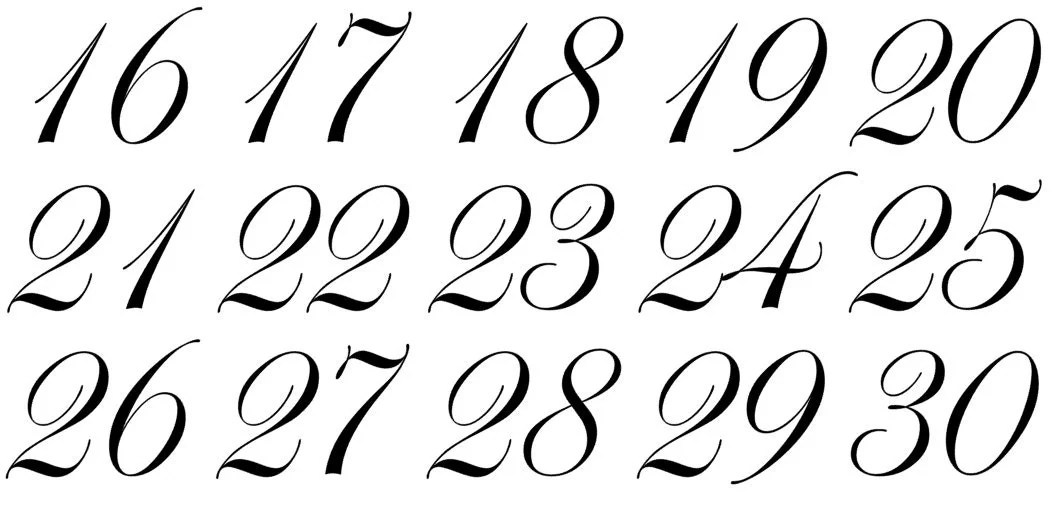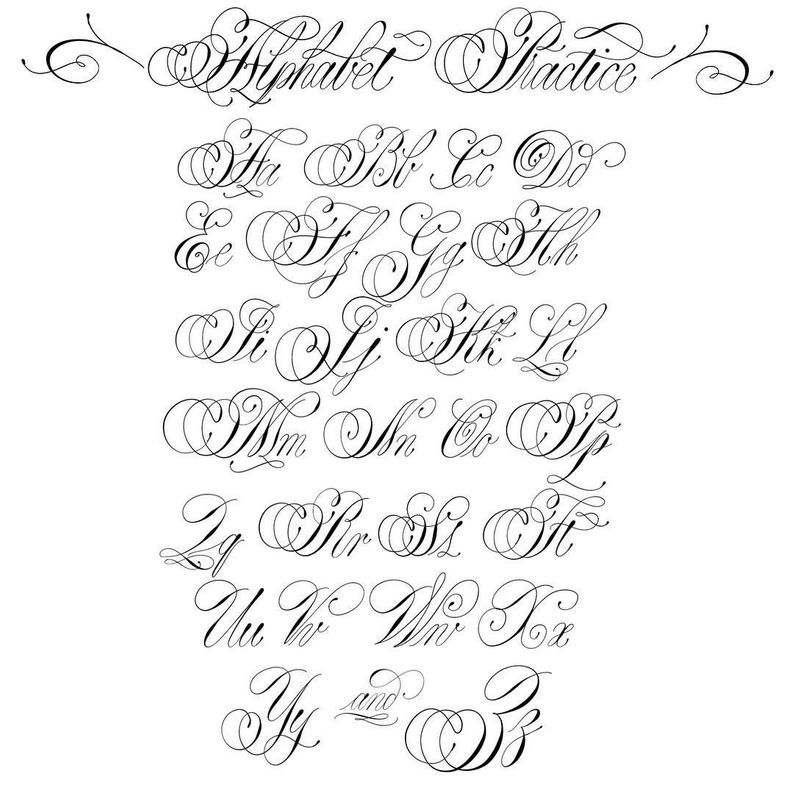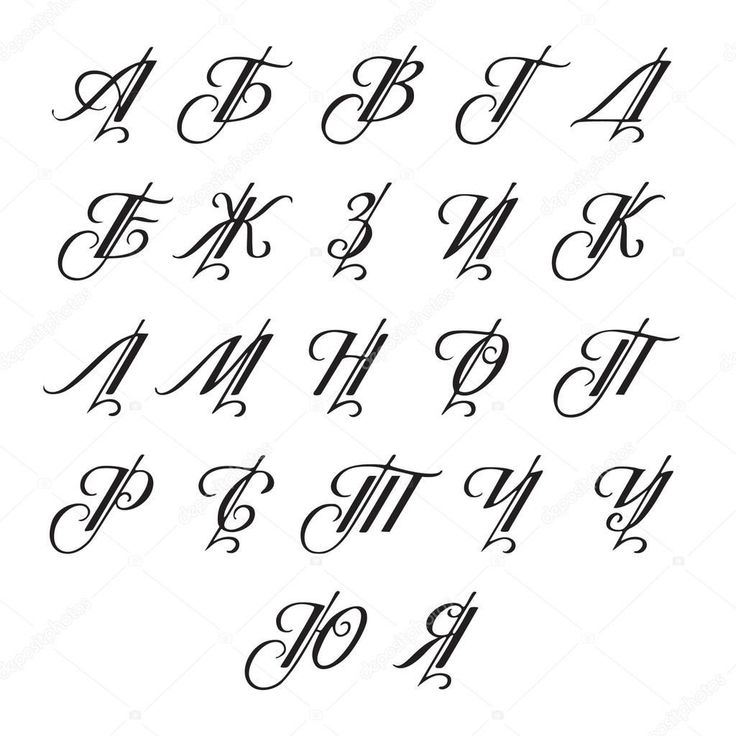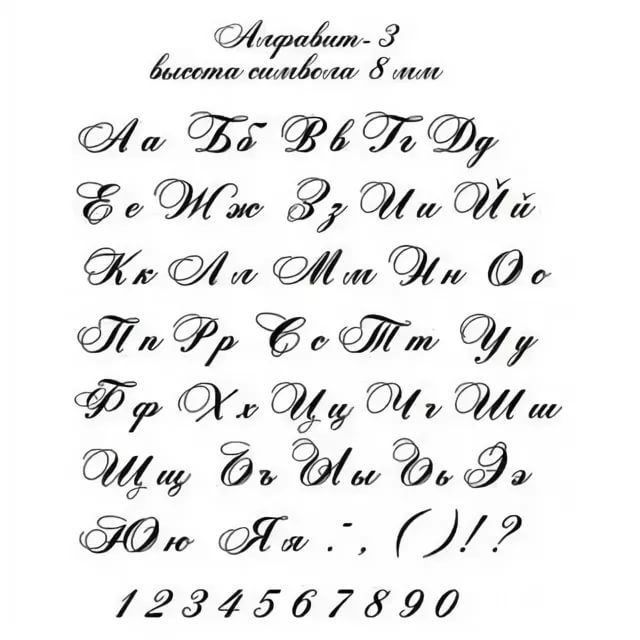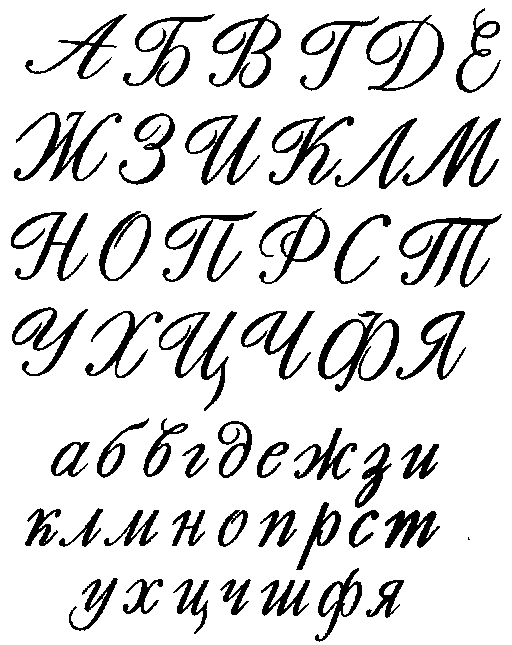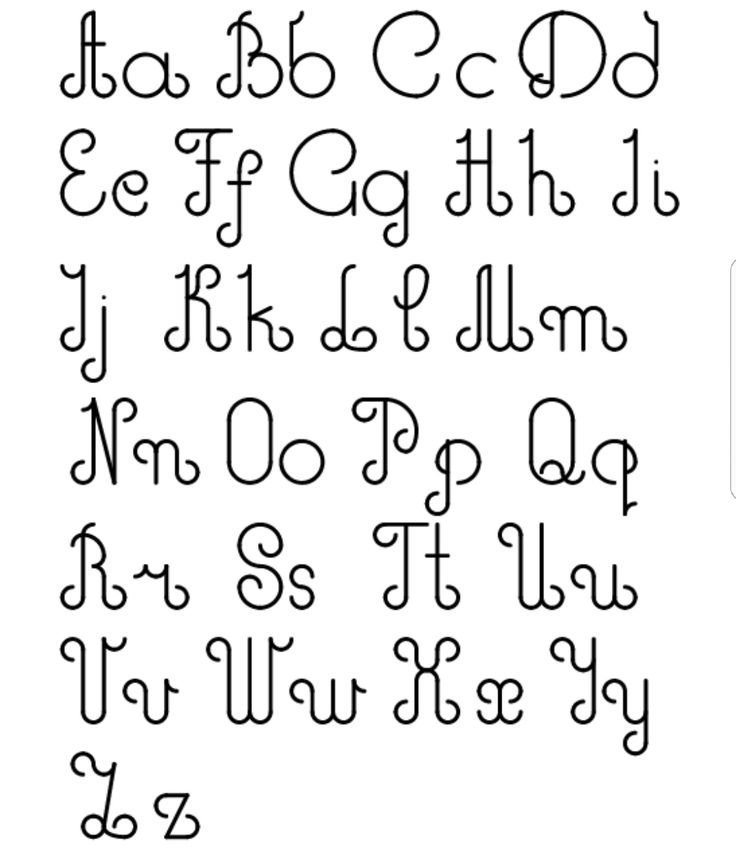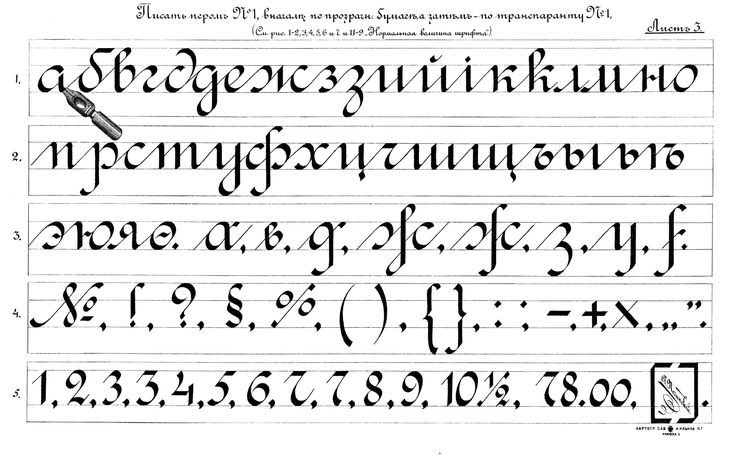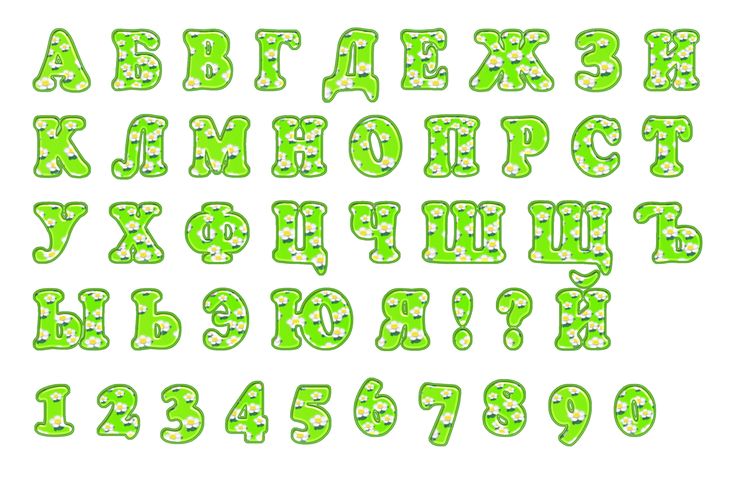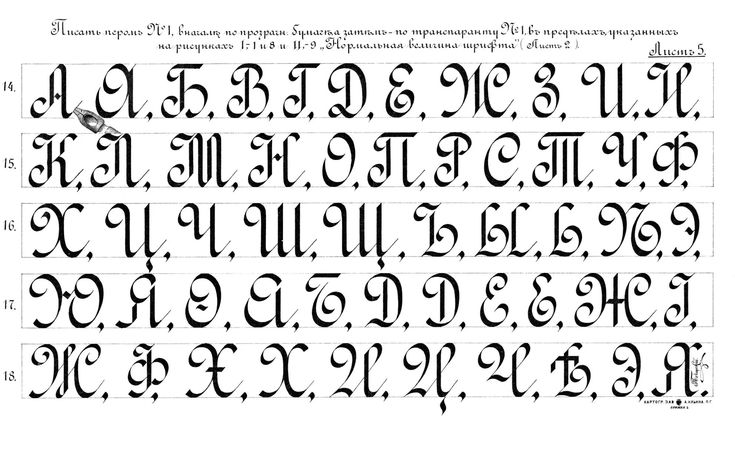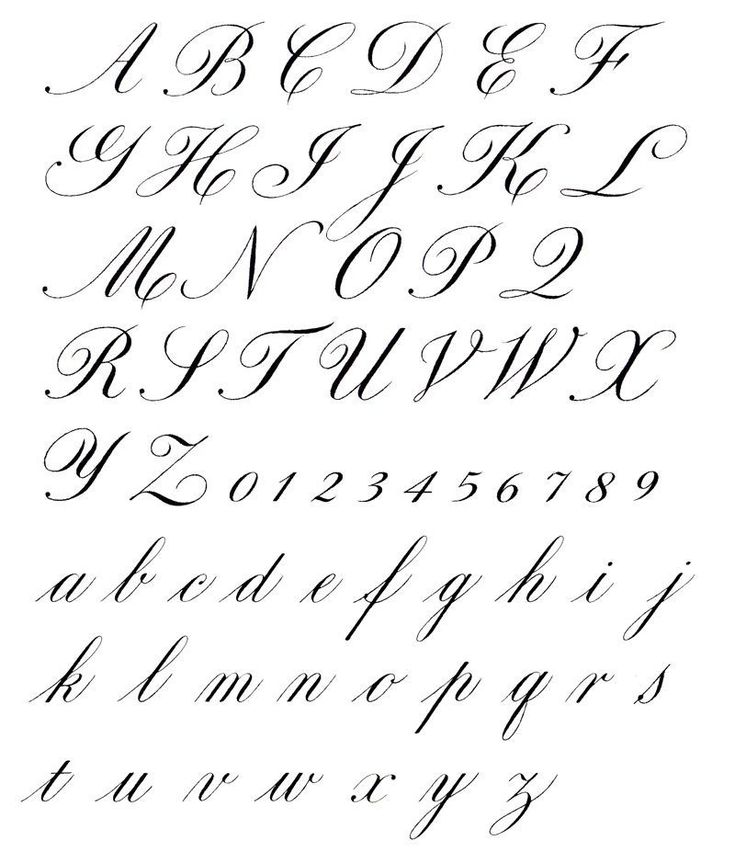
Красивые шрифты онлайн, сделать красивый текст
Шрифты являются важной частью типографики вашего проекта. Слишком причудливые буквы могут быть трудны для восприятия, слишком простые вызовут скуку и отобьют желание читать дальше. Вот почему следует максимально сосредоточиться на выборе красивых шрифтов, которые будут разборчивыми и привлекательными. Правильный фонт обеспечит эстетическую ценность контента, настроит общий тон проекта и пользовательский интерес.
Среди них вы найдете буквенно-цифровые наборы для любого случая и любой потребности, почти все начертания доступны для скачивания бесплатно. Нужен ли вам фонт для оформления проекта или просто хотите посмотреть, как будет выглядеть надпись красивым шрифтом онлайн — на нашем сайте есть все, что нужно. С таким количеством гарнитур вы обязательно найдете идеальный вариант для работы
Если никак не получается самостоятельно подобрать нужный стиль для дизайна текста, не волнуйтесь.
Мы позаботились о решении проблемы. На этой странице представлено много красивых шрифтов как для скачивания, так и для просмотра онлайн.
Все они отличаются индивидуальностью и разнообразием: среди них есть версии с засечками и без, рукописные, готические, курсив, печатные с поддержкой кириллицы. Цель использования таких фонтов — привлечь внимание оригинальным внешним видом. С помощью красивых шрифтов можно сделать авторскую надпись или заголовок, выделить часть текста, придав ему неповторимость и уникальность. Но для использования в основном контенте они не годятся.
Зачастую сложно определить, как будет смотреться тот или иной набор букв в проекте. Для этого нужно обладать большим опытом и фантазией. Если вы начинающий дизайнер или неискушенный любитель, попробуйте наш генератор красивых шрифтов онлайн. Просто напишите свой текст в форме для ввода, нажмите клавишу «Применить» и выбирайте понравившейся стиль из сотни предложенных.
К сожалению, некоторые из предложенных стилей не поддерживают русский язык, поэтому получить надпись кириллицей не всегда получается. Но таких фонтов совсем мало. С их помощью можно оформить красивый текст с элементами английского языка, что также необходимо в дизайне.
Начните работу с Ffont.ru уже сегодня и найдите шрифты, которые обязательно будут соответствовать вашему образу!
50 бесплатных современных шрифтов — UXPUB
Если вы ищете великолепный и стильный шрифт, посмотрите на эту современную подборку.
Этот обзор полон элегантных, стильных и универсальных шрифтов. Он идеально подойдут для всех видов современного дизайна, от веб-сайтов до печатных материалов.
Мы также хотим убедиться, что вы понимаете, что на самом деле означает «бесплатный», когда речь идет о шрифтах и типографике. Дизайнеры шрифтов иногда предлагают свои шрифты совершенно бесплатно для личного и коммерческого использования.
Некоторые предлагают их бесплатно только для личного использования, а другие предлагают только демоверсию, а полная версия доступна после покупки лицензии. Поэтому обязательно ознакомьтесь с деталями, прежде чем использовать представленные ниже шрифты в своих проектах.
Leoscar
Этот современный набор шрифтов, разработанный Faridul Haque, имеет версии с засечками и без. Набор без засечек аккуратный и четкий, с разными стилями и прямыми углами. Версия с засечками имеет тонкие, небольшие удлинители с аккуратным изогнутым соединением. Строчные буквы Leoscar округлены и изящны и будут хорошо смотреться в небольших абзацах.